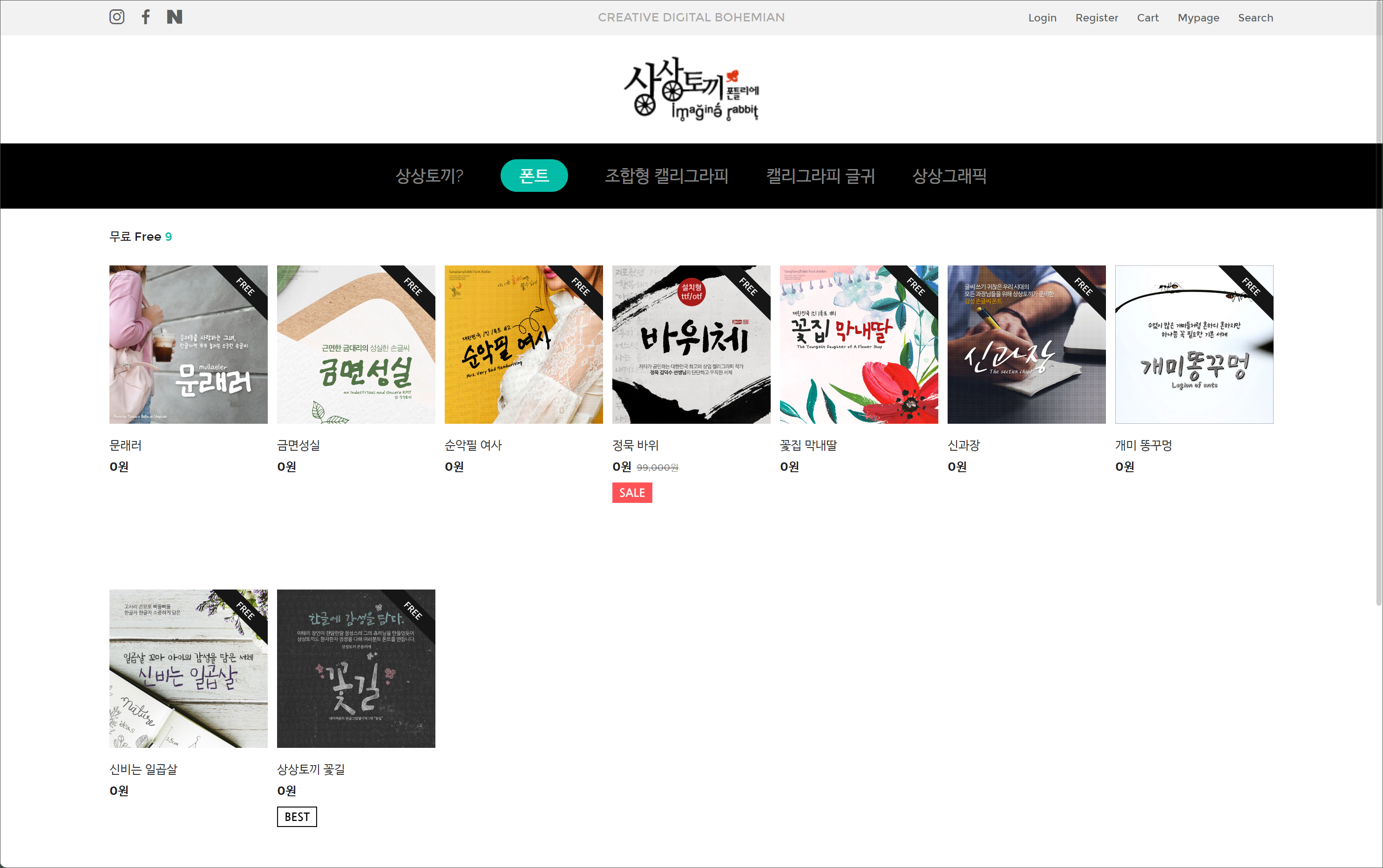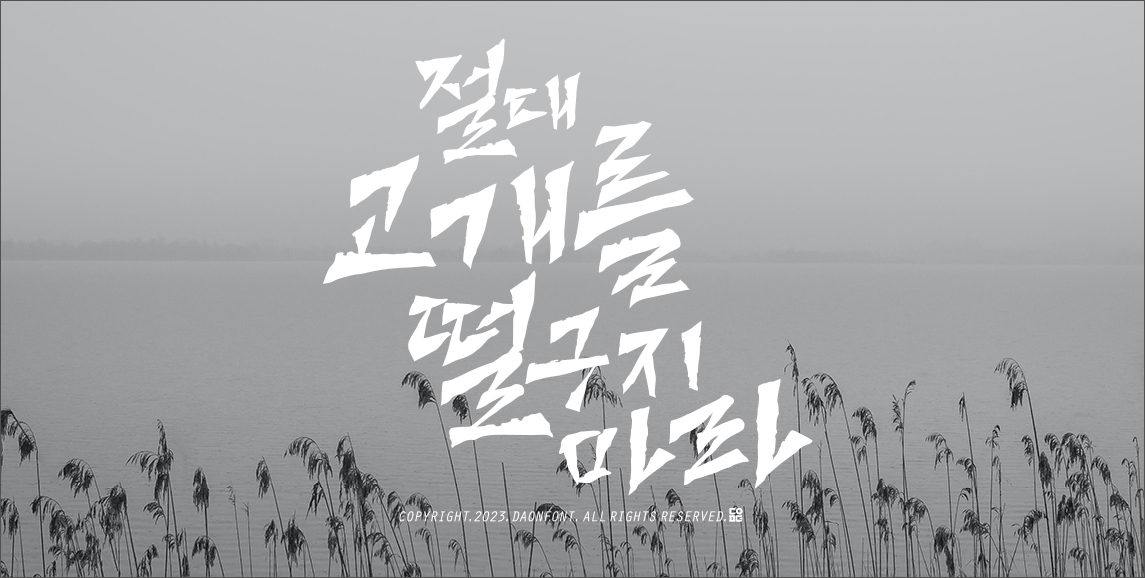
캘리그래피(Calligraphy)는 글씨나 글자를 아름답게 쓰는 기술을 뜻합니다. 손글씨로 쓰는 것이 일반적이지만, 다양한 요구에 따라 캘리그래피 스타일의 폰트들이 개발되고 있습니다.
네이버 나눔 손글씨 폰트
손글씨가 네이버의 클로바 AI 기술을 만나 109종이나 되는 새로운 글꼴이 탄생했습니다.
기억에 남을 나만의 명함, 생일 축하 카드, 청첩장 등 다양하게 활용할 수 있습니다.
다온폰트 밀양아리랑체
밀양시, 밀양문화재단에서 제작한 캘리그래피 스타일의 폰트로 서체의 변형이 없이 그대로 사용하는 조건으로 무료 사용이 가능합니다.
다온폰트 228
우리나라의 최초 민주운동인 2.28 민주운동을 기념하기 위하여 제작된 폰트로 무료 사용이 가능합니다.
B, M, L 3가지 두께를 지원하며 서체의 스케일을 조정하여 캘리그라피 느낌으로 사용할 수 있습니다.
다온폰트 신라문화체
경주시청에서 제작한 폰트로 575돌 한글날을 기념하여 무료로 배포되고 있습니다.
B, M 2가지 두께를 지원하며, 붓글씨의 거친 질감을 표현한 서체로 제목에 사용하기 좋은 폰트입니다.
상상토끼 캘리그라피 폰트
상상토끼는 캘리그라피 작가로 활동하며 직접 폰트를 만드는 그래픽 아티스트입니다.
문래러, 금면성실, 순악필 여사, 정묵 바위, 꽃집 막내딸, 신과장, 개미 똥꾸멍, 신비는 일곱살, 상상토끼 꽃길 등 9종의 캘리그래피 스타일의 폰트를 무료로 제공하고 있습니다. 기업이나 개인 상업적 이용이 가능합니다.
눈누 캘리그래피 폰트
'눈누'는 상업적으로 이용할 수 있는 한글 폰트 무료 한글 폰트를 모아 많은 사람들에게 소개하기 위해 만들어진 사이트로 무료로 이용이 가능한 다양한 한글 폰트를 소개하고 있습니다.
학교안심 가을소풍, 밀양영남루체, 밀양해맑은상상체, 밀양아리랑체, KCC안중근체, KCC박경리체 등 6종의 캘리그래피 스타일의 폰트를 다운로드할 수 있습니다.